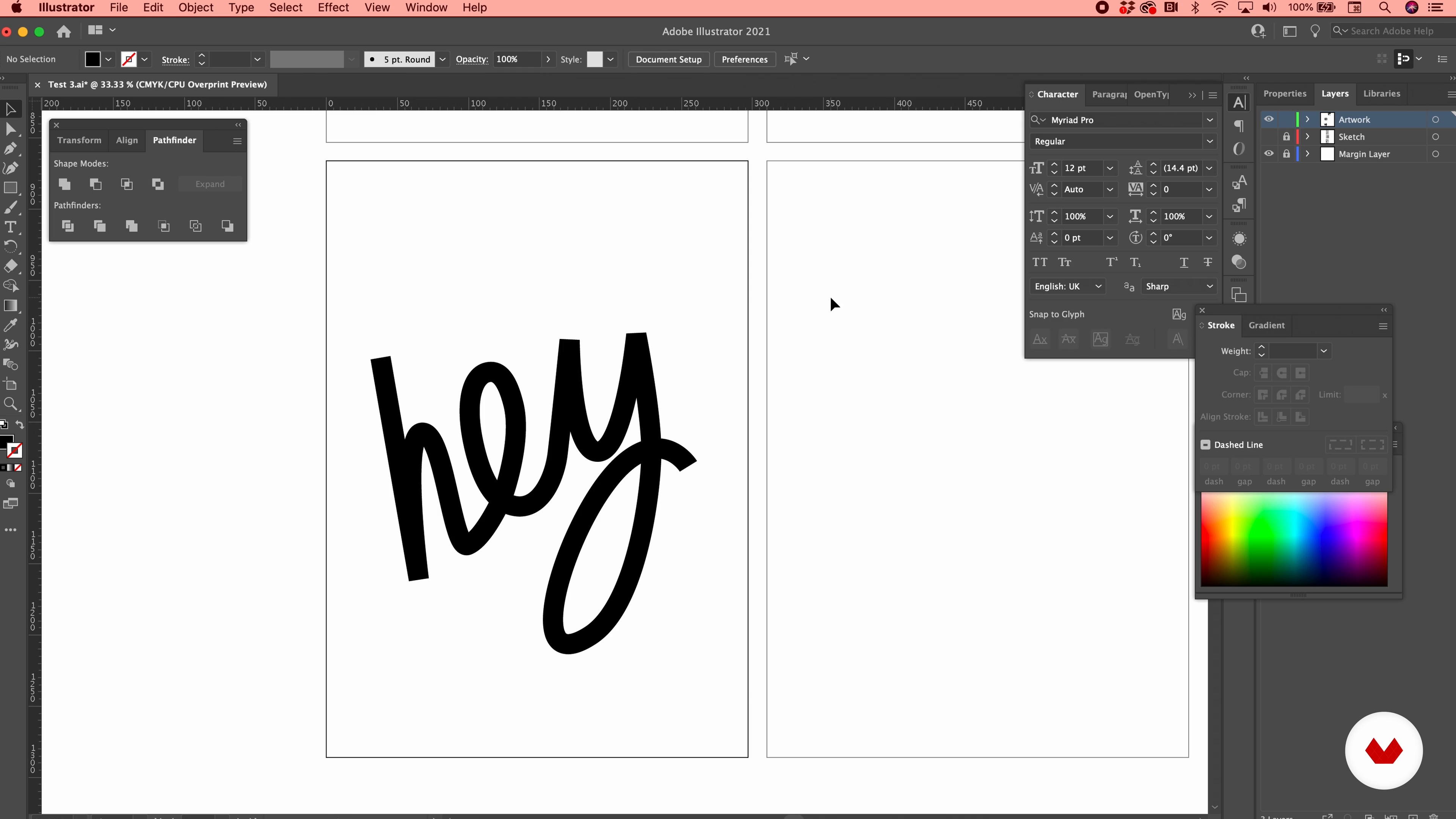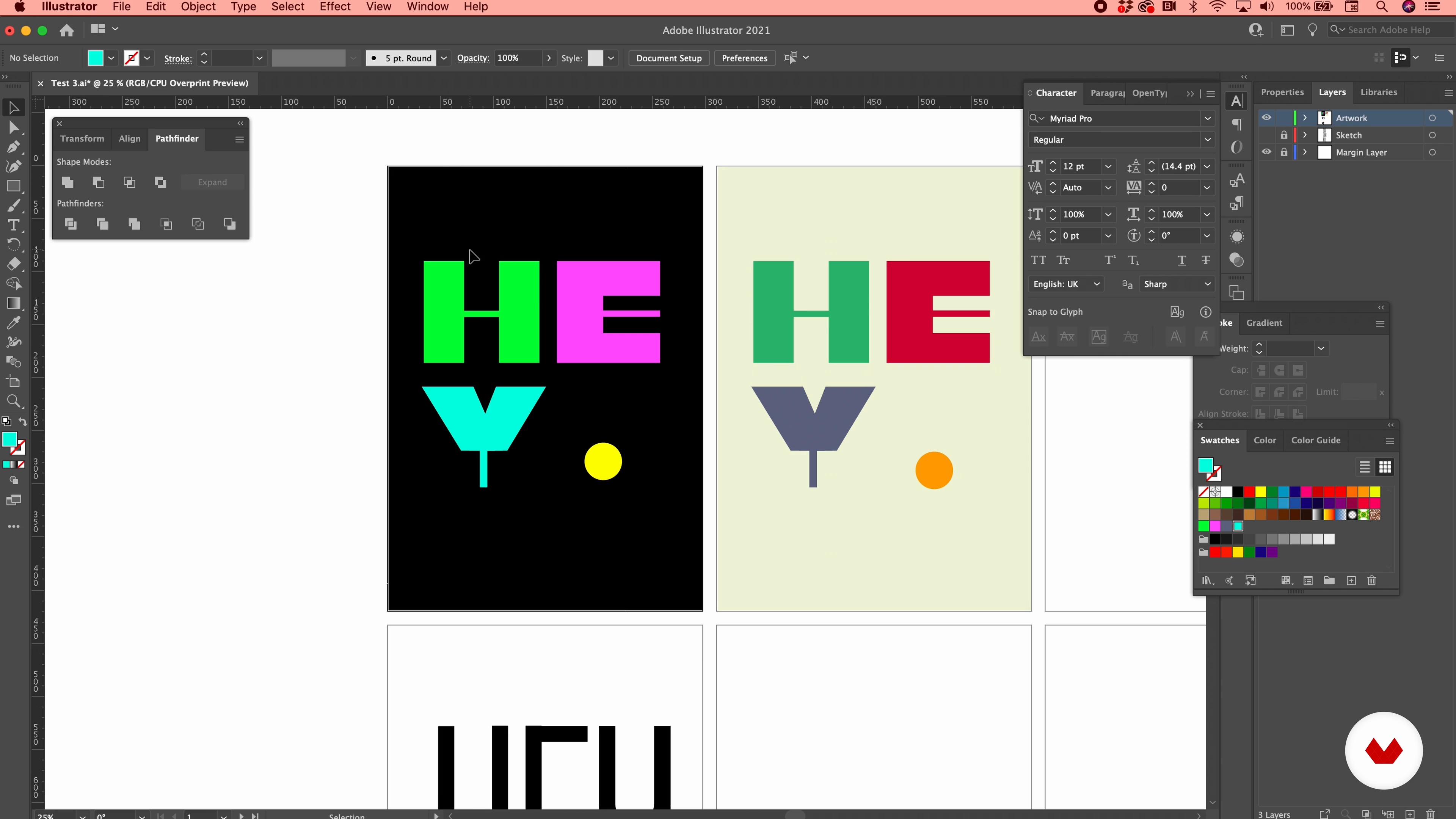
La typographie créative vous permet de relever certains défis de la vie et de les transformer en messages d'espoir, d'action et de positivité. Graphiste et typographe Dani Molyneux est passionnée par les mots et la beauté de les exprimer. Elle a travaillé pour de grandes agences de création à travers le Royaume-Uni et est la fondatrice de son propre studio, Dotto.
Dans ce cours, elle vous apprend à concevoir votre propre typographie audacieuse, colorée et ludique. Créez une affiche contenant un message qui signifie quelque chose pour vous en utilisant votre propre type avec Dani comme guide. Explorez la typographie et créez des illustrations qui parlent !
Commencez par faire la connaissance de la graphiste et typographe Dani Molyneux. Elle parle de la carrière créative qui l'a amenée à créer sa propre marque, ainsi que des influences qui inspirent le travail qu'elle crée.
Jetez un œil à la façon dont la typographie peut représenter une humeur et choisissez un message pour votre pièce en gardant cela à l'esprit. Expérimentez avec la composition en créant vos croquis initiaux, puis configurez votre espace de travail numérique dans Illustrator. Découvrez différentes techniques pour créer des caractères et choisir une palette de couleurs.
Numérisez votre croquis, vectorisez-le, puis utilisez les techniques que vous avez apprises pour créer vos lettres. Explorez différentes combinaisons de couleurs pour votre pièce finale avant d'apporter la touche finale à votre affiche en vue de l'impression.
Découvrez différentes façons d'imprimer votre design, y compris l'impression Risograph. Ensuite, pour terminer le cours, Dani vous explique comment partager votre travail avec le monde, via les réseaux sociaux, votre portfolio, etc.
Créez une affiche typographique audacieuse et colorée sur un sujet qui vous tient à cœur.
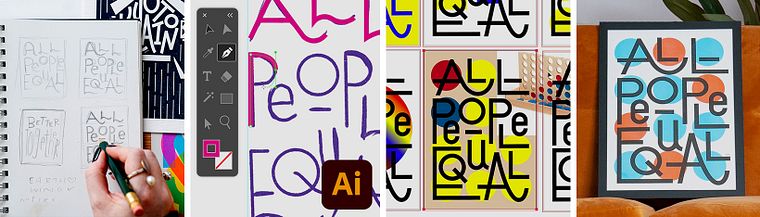
Ce cours s'adresse à toute personne intéressée par la conception de compositions typographiques ludiques avec des messages significatifs derrière eux.
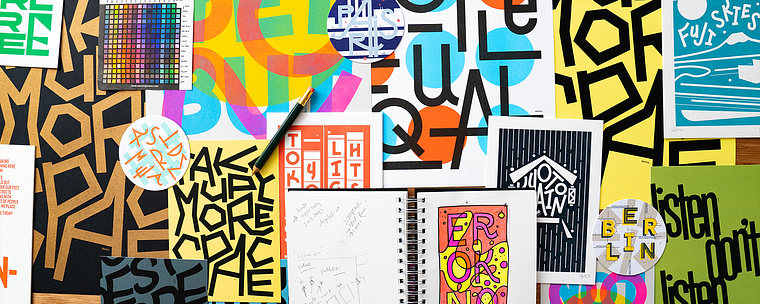
Vous apprendrez à créer des affiches typographiques expressives, développer des formes de lettres personnalisées, utiliser des palettes de couleurs minimalistes, configurer Illustrator pour l’impression, et optimiser votre flux de travail pour le numérique et l’impression.
Oui, le cours couvre les méthodes de travail du graphiste freelance et les étapes pratiques pour lancer une imprimerie, y compris la préparation des fichiers pour une impression professionnelle.
Oui, vous apprendrez à choisir des palettes de couleurs adaptées au numérique (RGB) et à l’impression (CMJN), y compris la sélection de couleurs Pantone et la gestion de la précision colorimétrique.
Vous pratiquerez la numérisation de croquis faits à la main, la modification des formes de lettres, et la création de typographies personnalisées avec les outils vectoriels d’Illustrator.